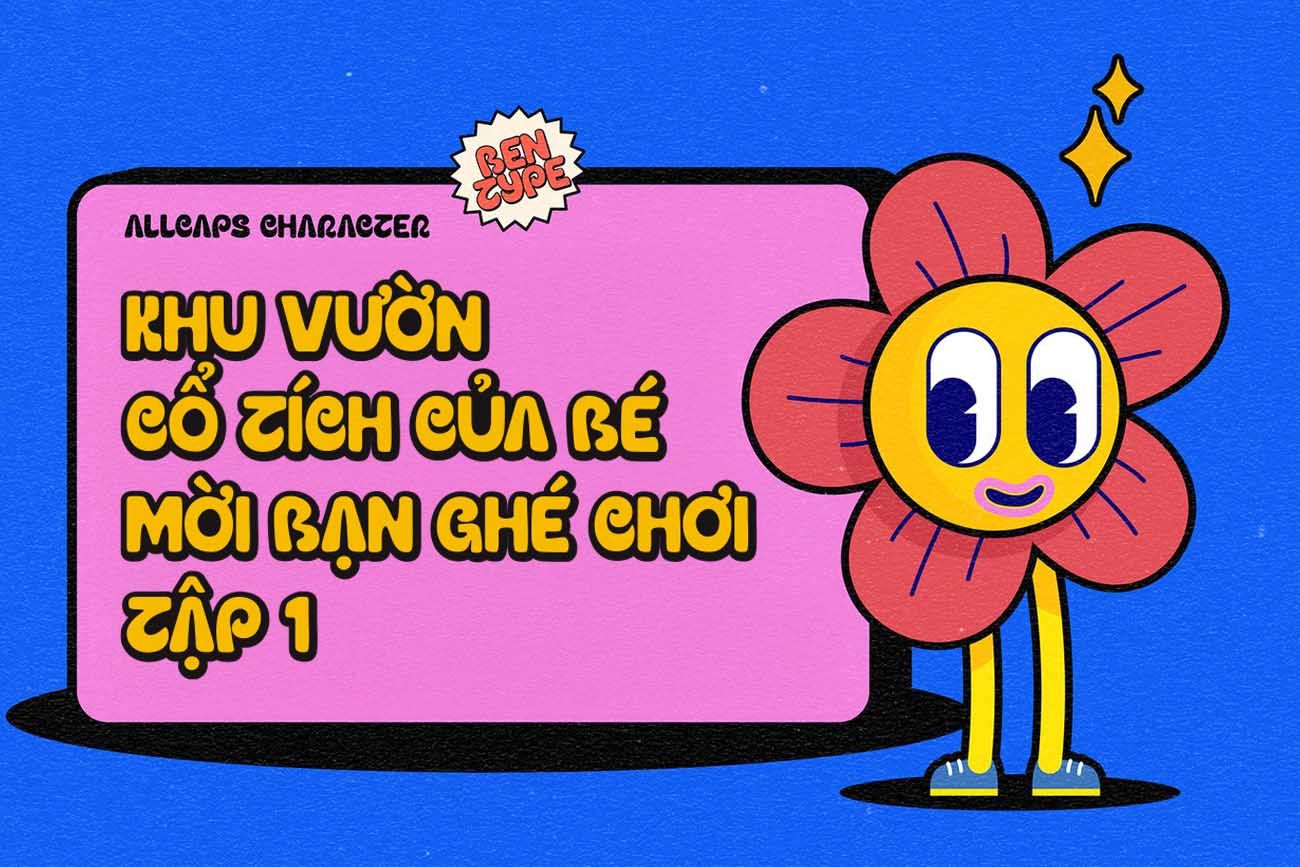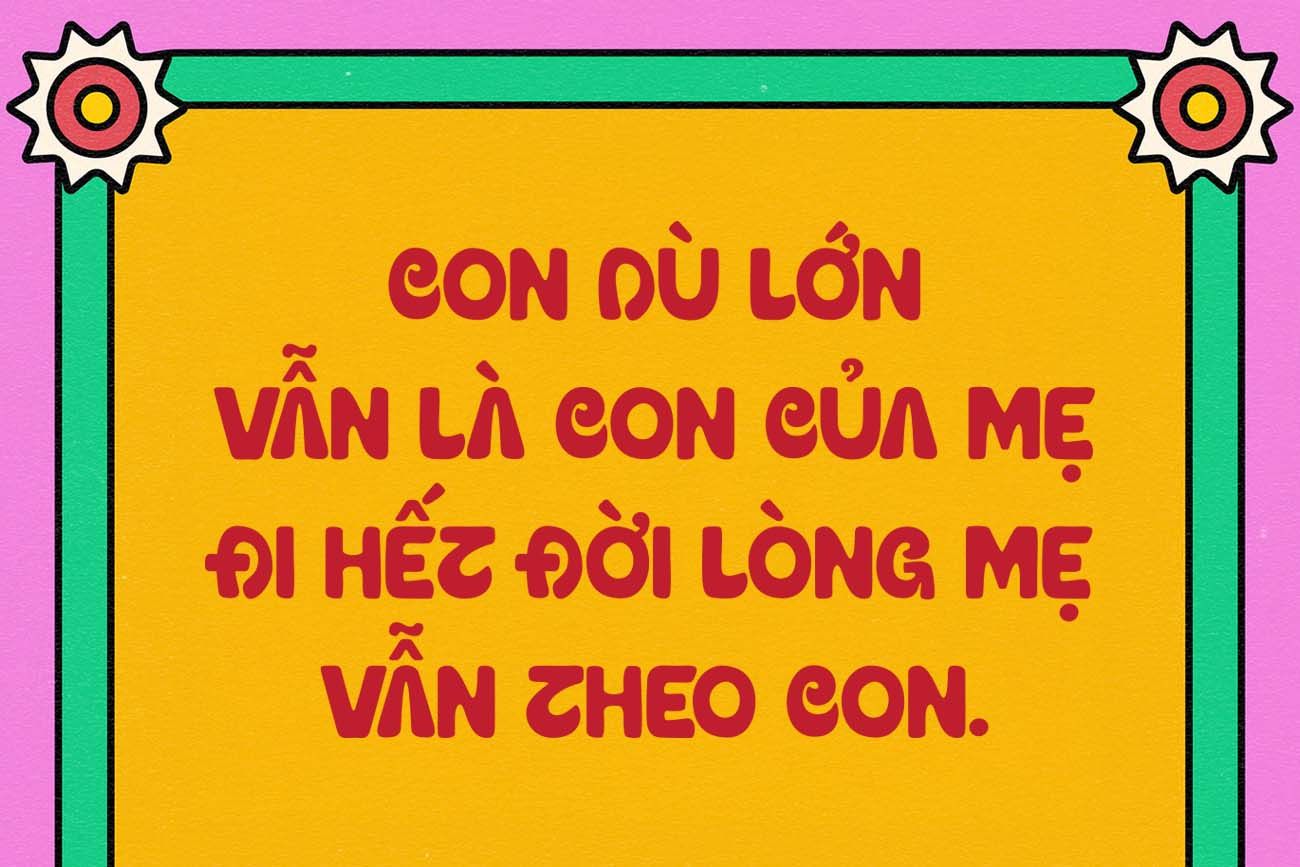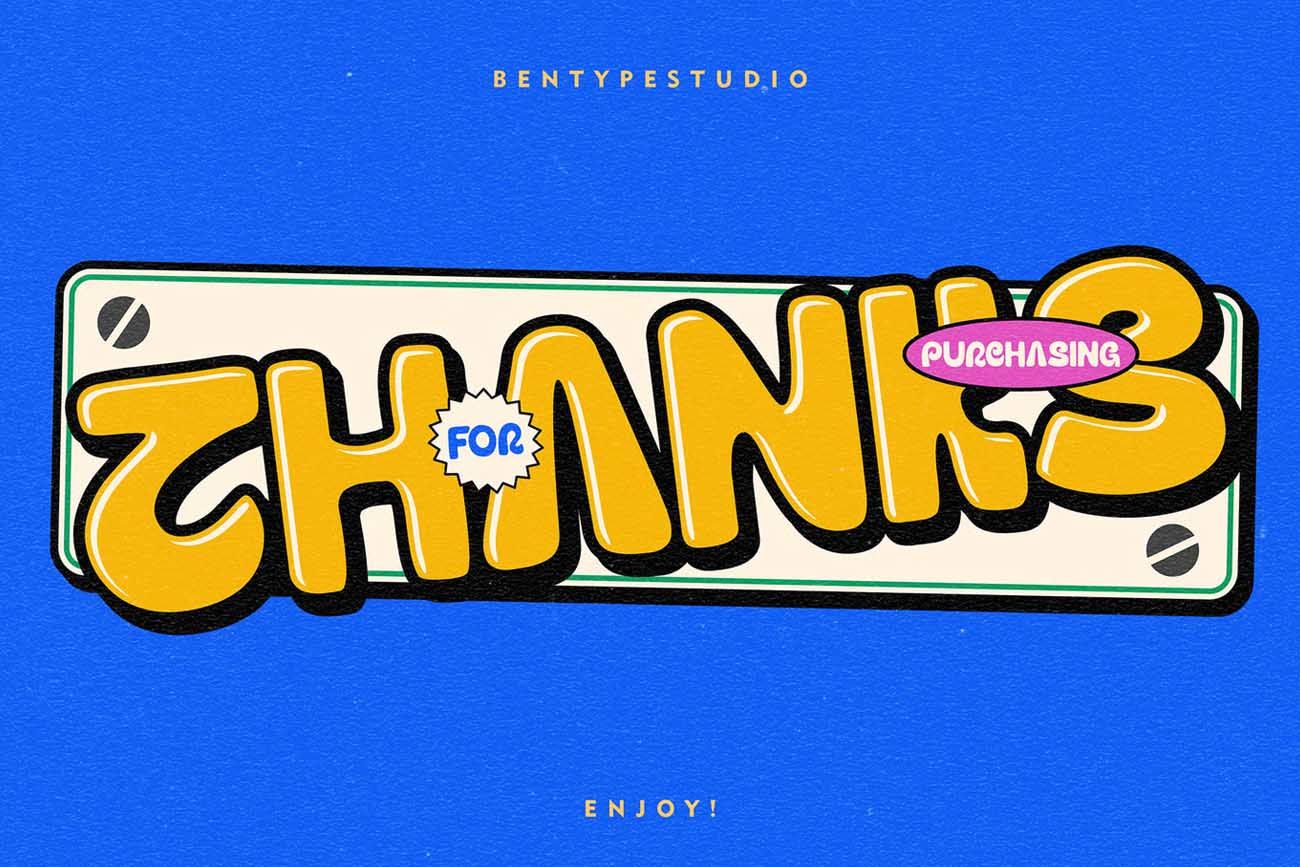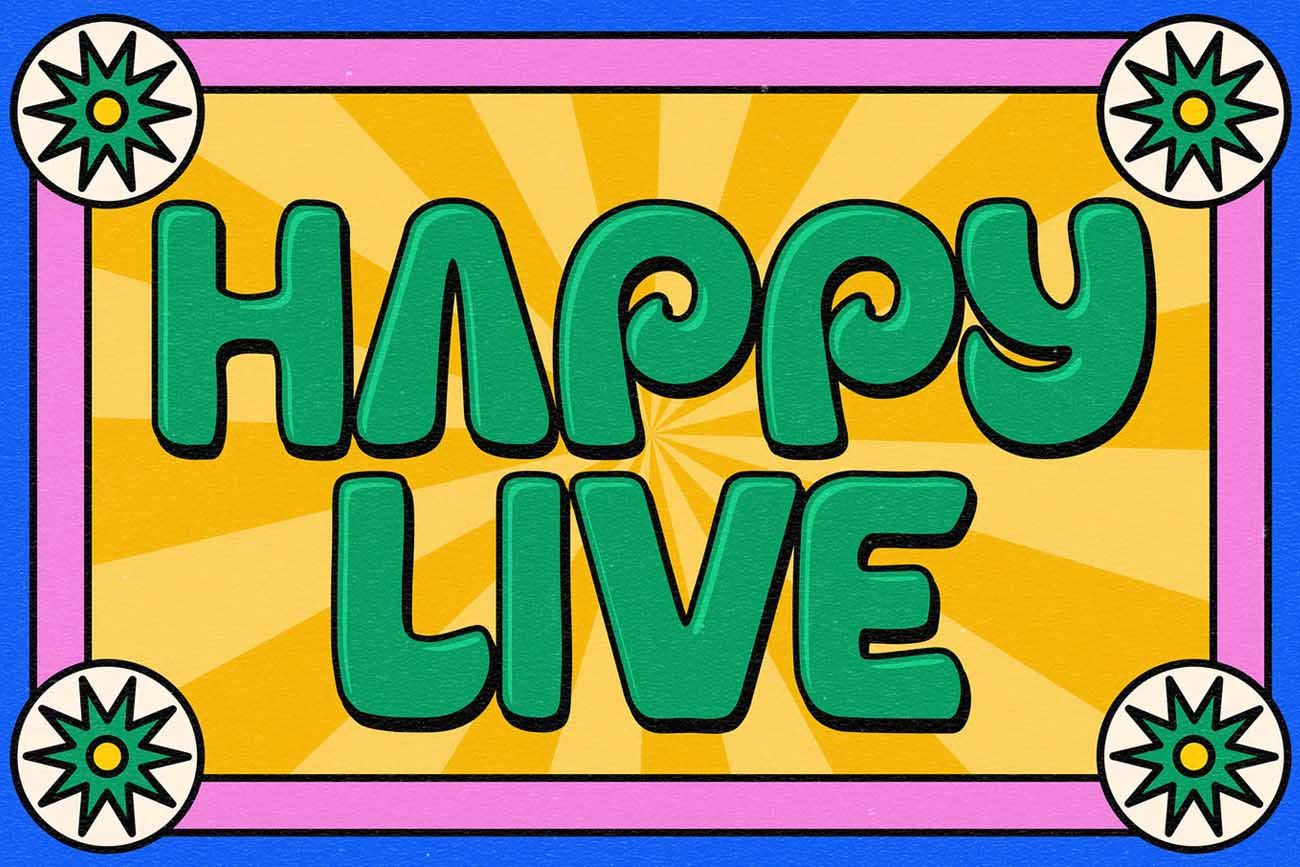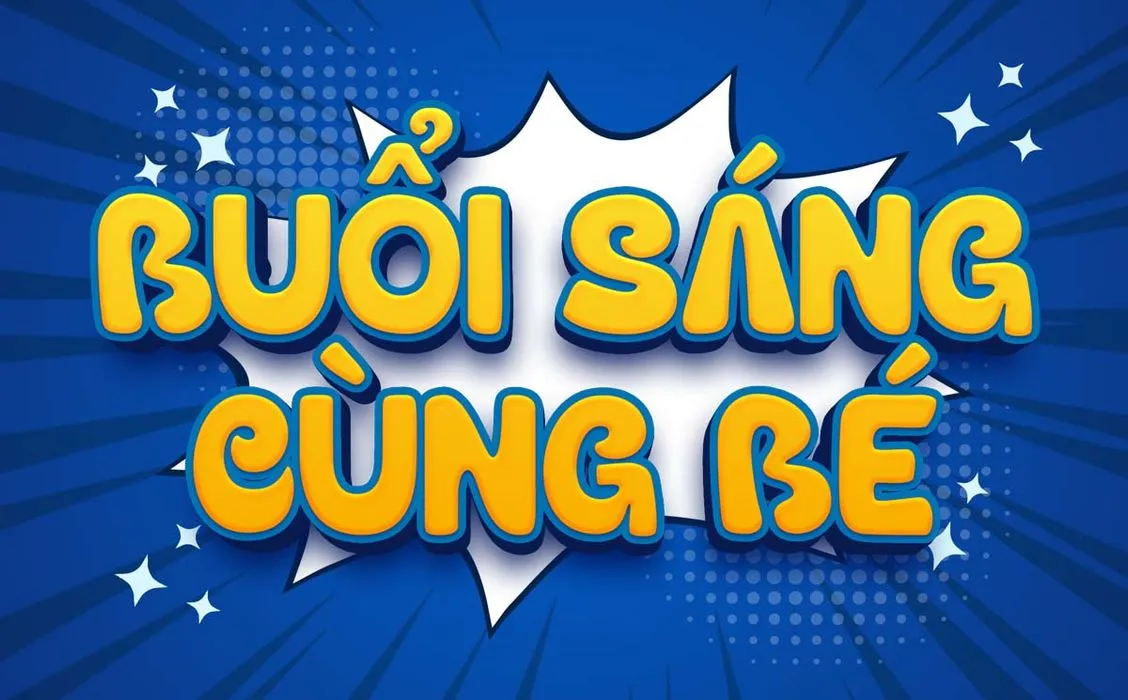
Bagyo Sans là một font chữ hoạt hình đầy năng lượng, mang phong cách retro bo tròn và nổi bật nhờ trọng lượng siêu đậm cùng các đường nét mềm mại, phồng căng như bong bóng. Được thiết kế bởi Ben Zype và phát hành bởi BENTYPE Studio, Bagyo Sans là lựa chọn lý tưởng cho những ai đang tìm kiếm một font chữ vui nhộn và cute.
Điểm nổi bật của TH Bagyo Sans:
• Thiết kế sans-serif siêu đậm, với các góc bo tròn hoàn hảo, tạo cảm giác mềm mại và thân thiện.
• Các ký tự được làm phồng, đổ bóng nhẹ theo phong cách bubble cartoon, cực kỳ bắt mắt khi sử dụng cho tiêu đề hoặc logo.
• Phong cách retro pha hoạt hình, mang hơi thở của văn hóa pop và các ấn phẩm dành cho trẻ em trong thập niên 90.
• Font đã được Việt hóa đầy đủ bởi Phạm Sơn – Admin của S99.vn và Fontdep.vn – đảm bảo hỗ trợ trọn bộ dấu tiếng Việt, giữ nguyên tinh thần vui nhộn và mềm mại của bản gốc.
• Phù hợp để kết hợp với các màu sắc rực rỡ, hiệu ứng nổi khối, tạo nên sự sinh động và dễ thu hút thị giác trẻ nhỏ.
Kiểu dáng font Bagyo Sans – Béo tròn, phồng căng & đậm chất hoạt hình
Bagyo Sans sở hữu kiểu dáng béo tròn và căng đầy, với từng chữ cái được thiết kế như thể được thổi phồng bằng hơi – mang lại cảm giác mềm mại, vui nhộn và cực kỳ “nổi”. Các nét chữ không sắc cạnh mà hoàn toàn bo tròn, tạo cảm giác thân thiện và dễ tiếp cận, đặc biệt hấp dẫn với đối tượng thiếu nhi.
Hiệu ứng đổ bóng và điểm highlight giả lập ánh sáng càng làm tăng chiều sâu thị giác, khiến font trở nên giống như các dòng chữ thường thấy trong truyện tranh, bìa đĩa hoạt hình hay biển quảng cáo retro. Phần thân chữ dày đều, các khoảng cách được thiết kế chặt chẽ nhưng vẫn dễ đọc – giúp Bagyo Sans phù hợp cho cả tiêu đề lẫn nhãn dán.
Kiểu dáng này tạo nên một tổng thể ngộ nghĩnh, tươi sáng và cực kỳ hút mắt, lý tưởng cho các thiết kế đậm chất pop-art, vui tươi và phá cách.
Gợi ý ứng dụng:
• Tiêu đề poster hoạt hình, tạp chí thiếu nhi, banner sản phẩm vui chơi
• Thiết kế bao bì snack, đồ chơi, sản phẩm dành cho trẻ em
• Logo các thương hiệu mang phong cách retro, năng động, trẻ trung
• Trò chơi điện tử, ứng dụng di động hoặc giao diện vui nhộn
Với phong cách sống động và thiết kế bắt mắt, Bagyo Sans là font chữ không thể thiếu nếu bạn đang xây dựng dự án dành cho trẻ nhỏ hoặc muốn tạo nên một bản thiết kế thật tươi vui và bùng nổ cá tính.